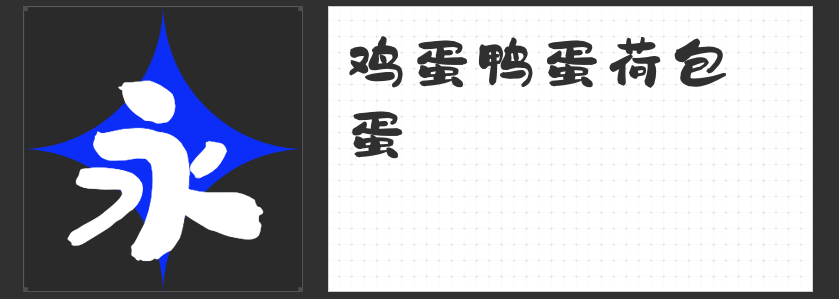
四款萌系字体推荐:用可爱笔触唤醒设计中的童真魔法
在儿童绘本、文创包装或品牌IP设计中,如何通过字体传递温暖治愈的视觉语言?以下四款风格各异的可爱字体,以圆润笔触与灵动结构,为设计注入天真烂漫的童趣灵魂。
一、MyFont郑明瑾卡通简
这款字体以饱满的字形构建视觉舒适区,自然的弧线与柔和转角让每个字符仿佛自带微笑表情。其设计精髓在于“刚刚好的圆润”——既保留了手写体的温度,又通过标准化处理确保远距离可读性。无论是儿童书籍标题的童真演绎,还是母婴品牌包装的温柔叙事,都能以无攻击性的视觉语言拉近与受众的距离。
二、励字小星星简
当拙朴线条邂逅现代装饰趣味,这款字体以“不完美中的完美”诠释童稚美学。刻意保留的手写肌理与均匀布白形成微妙平衡,使其既能驾驭动漫IP的Q版人设海报,也能完美融入文创产品的手账风格设计。特别适合需要营造“返璞归真”氛围的场景,让观者瞬间穿越回用蜡笔涂鸦的童年时光。
三、字圈也字多肉体
突破传统汉字结构的创新设计,将方框笔画转化为流动的圆环,创造出独特的“字形剧场”。这种“破方为圆”的智慧,让“口”字像气球、“目”字如镜头,天然适配儿童动画海报、教育类APP界面等需要强场景感的设计。字体自带的故事性,让信息传递超越文字本身,成为视觉叙事的参与者。
四、高手兵克笨笨体
在严谨的汉字框架中注入松弛感,这款字体通过微妙的笔画错位与圆角处理,营造出孩童学字时的稚拙趣味。其设计哲学恰似“有控制的随意”,既保持品牌传播所需的辨识度,又用灵动的结构打破常规排版束缚。特别适合休闲食品包装、儿童乐园导视系统等需要传递轻松氛围的场景。
从手绘温度到结构创新,这四款字体以不同维度诠释可爱设计的可能性。当商业项目需要唤醒受众的童心记忆时,它们将成为打破同质化、建立情感共鸣的秘密武器。